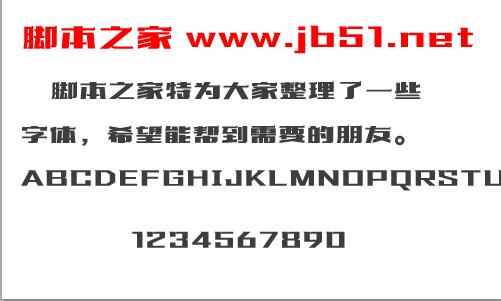
方正剛毅體是一款粗獷有力,個(gè)性鮮明的標(biāo)題字體。字形整體,堅(jiān)實(shí)而剛毅,果斷而積極,橫豎線筆畫(huà)對(duì)比強(qiáng)烈,張力十足,充滿了力量感和氣勢(shì)感。本款字體適用于海報(bào)、廣告、banner等標(biāo)題環(huán)境中。